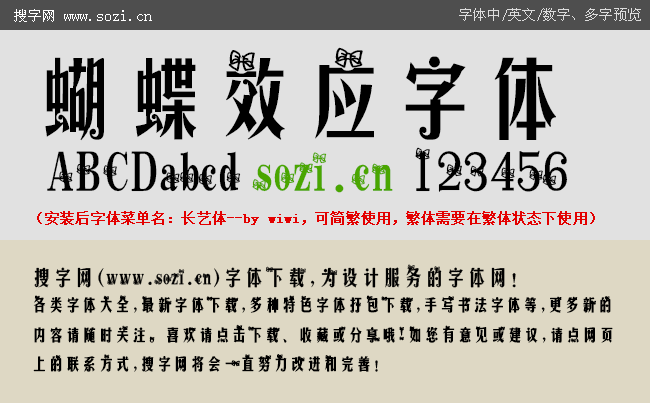
蝴蝶效應字體
搜字網給大家提供一款蝴蝶效應字體手機中文字體下載。這款手機字體是在漢儀長藝體筆畫間插入了卡通蝴蝶圖案。長藝體既有黑體的粗壯醒目,又有宋體的秀美柔和,加上藝術性的圓球形點、起筆如蝌蚪形的頓點、螺螄轉似的小鉤,配以修長的字形,如少女般婷婷玉立,裊娜動人,美觀而不落俗套。加入了卡通圖案后又增添了藝術性,特別適合喜歡手機字體個性一些的朋友在手機上安裝使用。